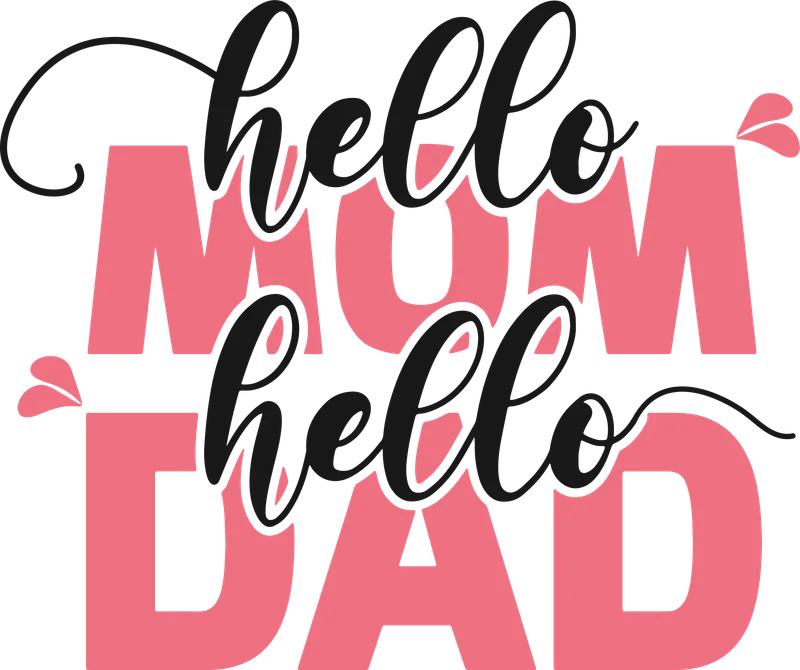
Lời chào "Hello Mom Dad" font chữ mềm mại
Lời chào "Hello Mom Dad" font chữ mềm mại — Thiết kế "Hello Mom Dad" độc đáo với font chữ thư pháp đen nổi bật trên nền hồng và xám. Thích hợp in áo gia đình, quà tặng ý nghĩa.
Trong hình có: chữ viết, lời chào
Phong cách: flat-design · Cảm giác: vui
Tông màu chủ đạo: xám, hồng